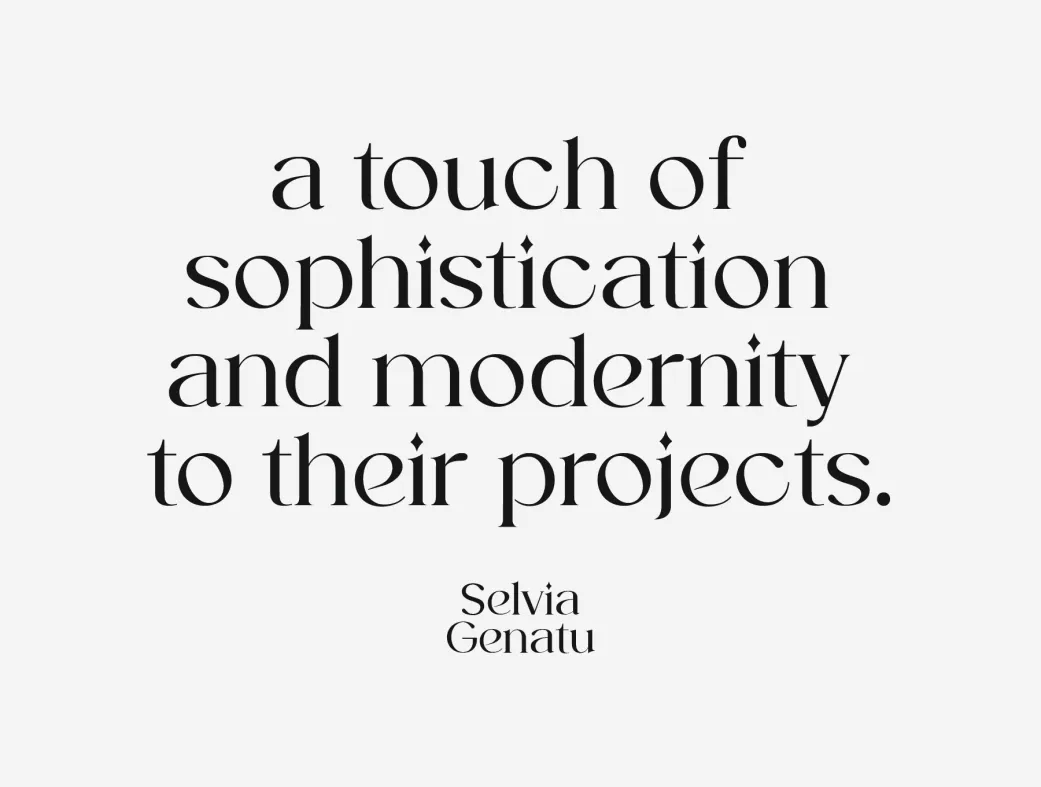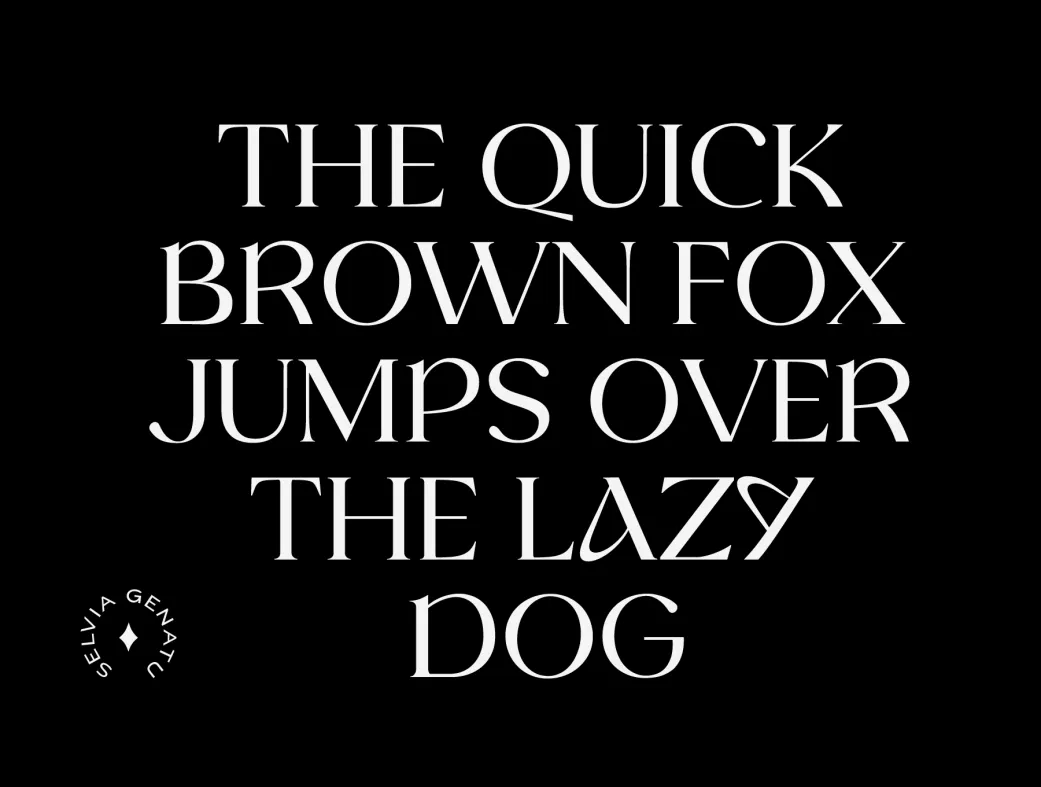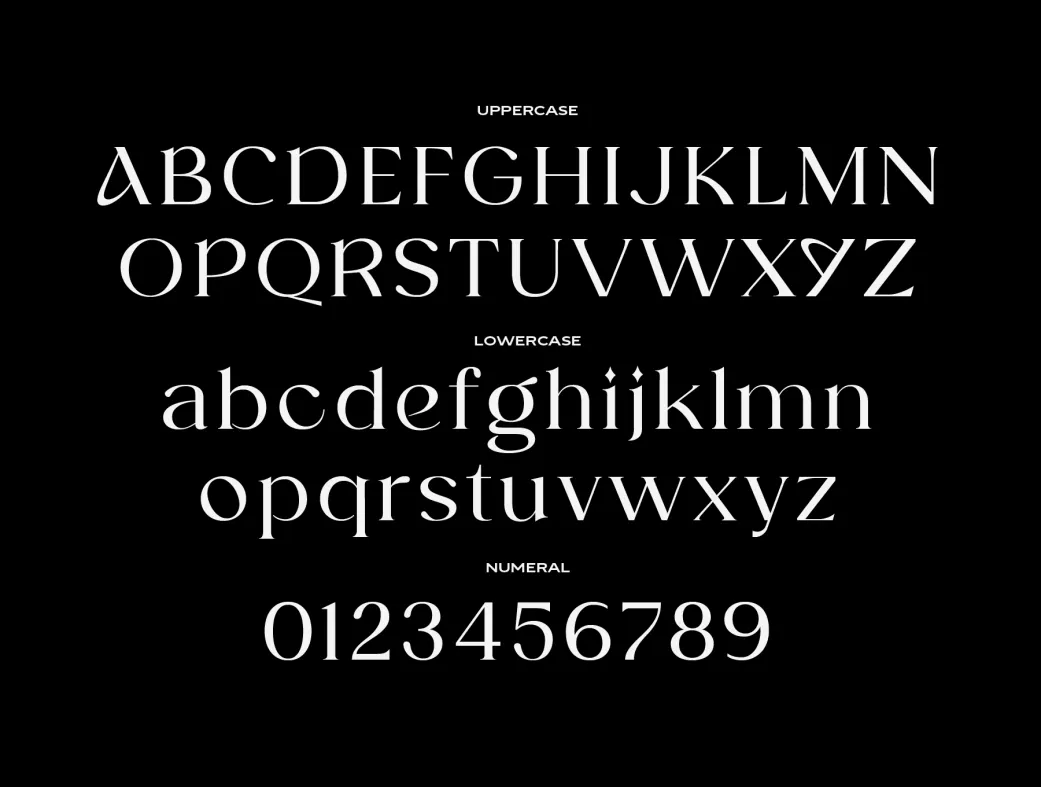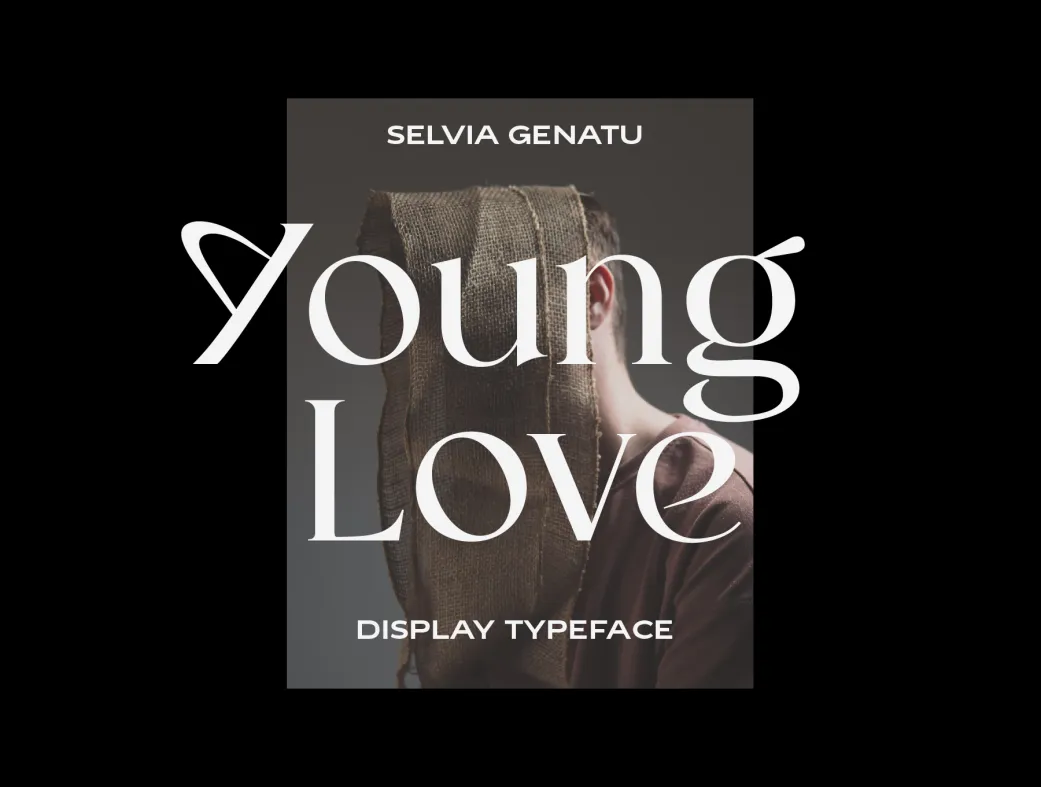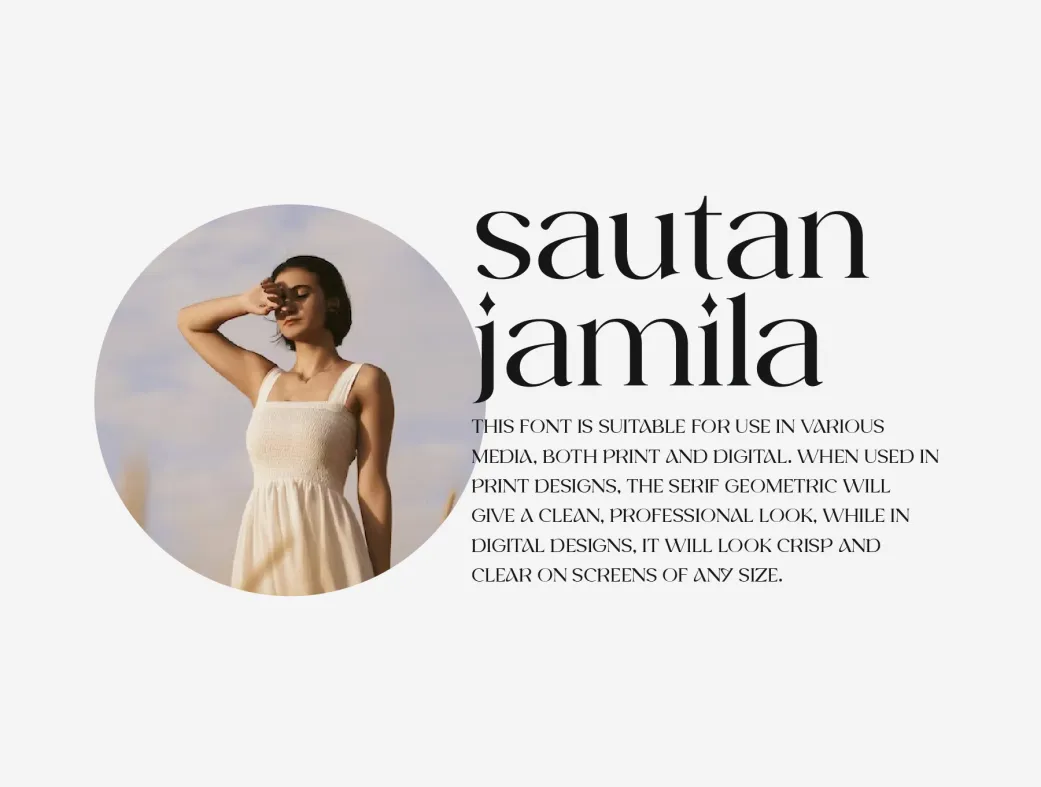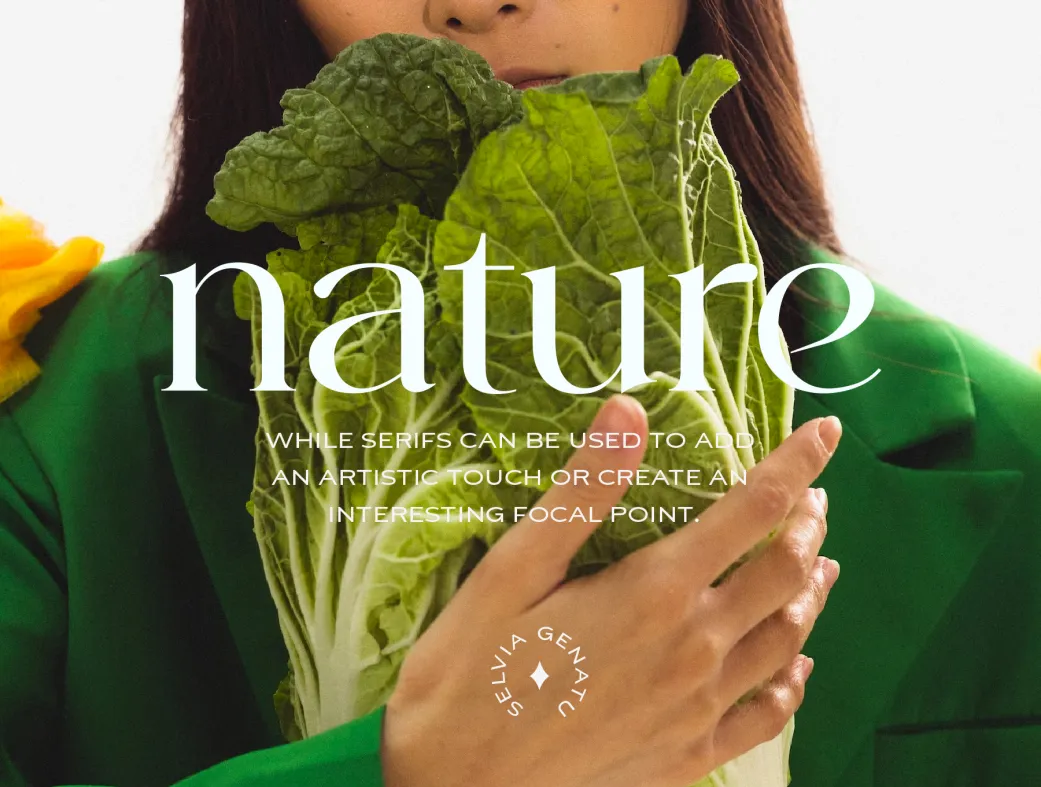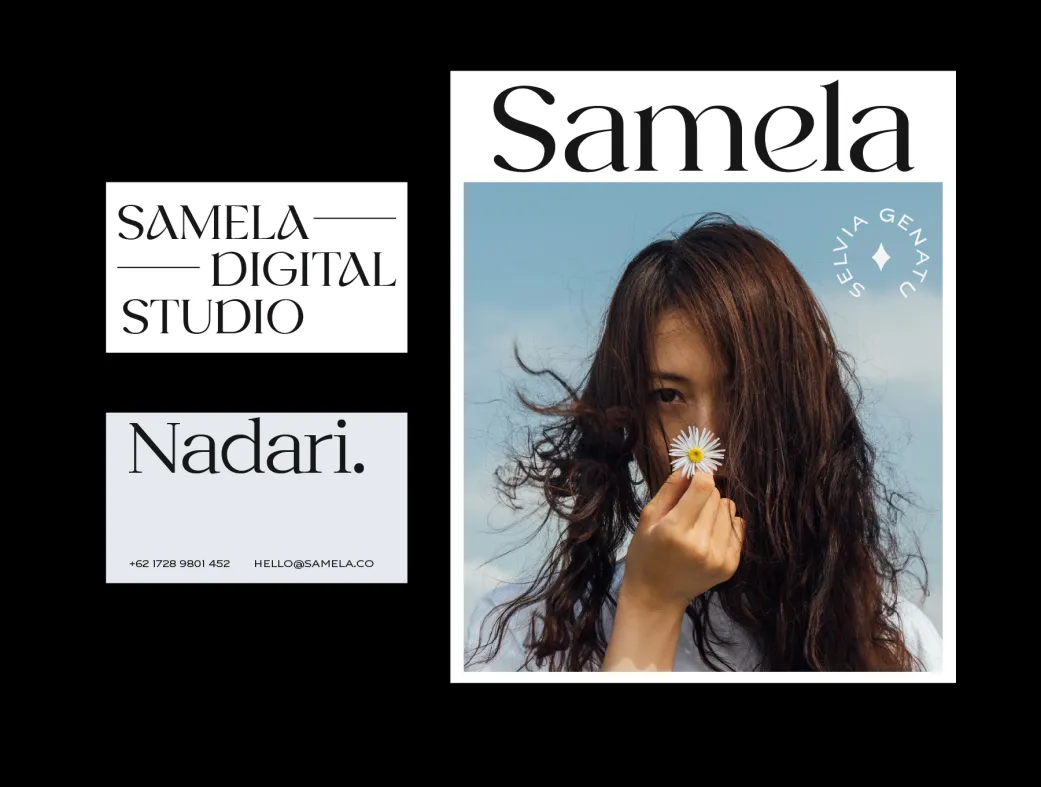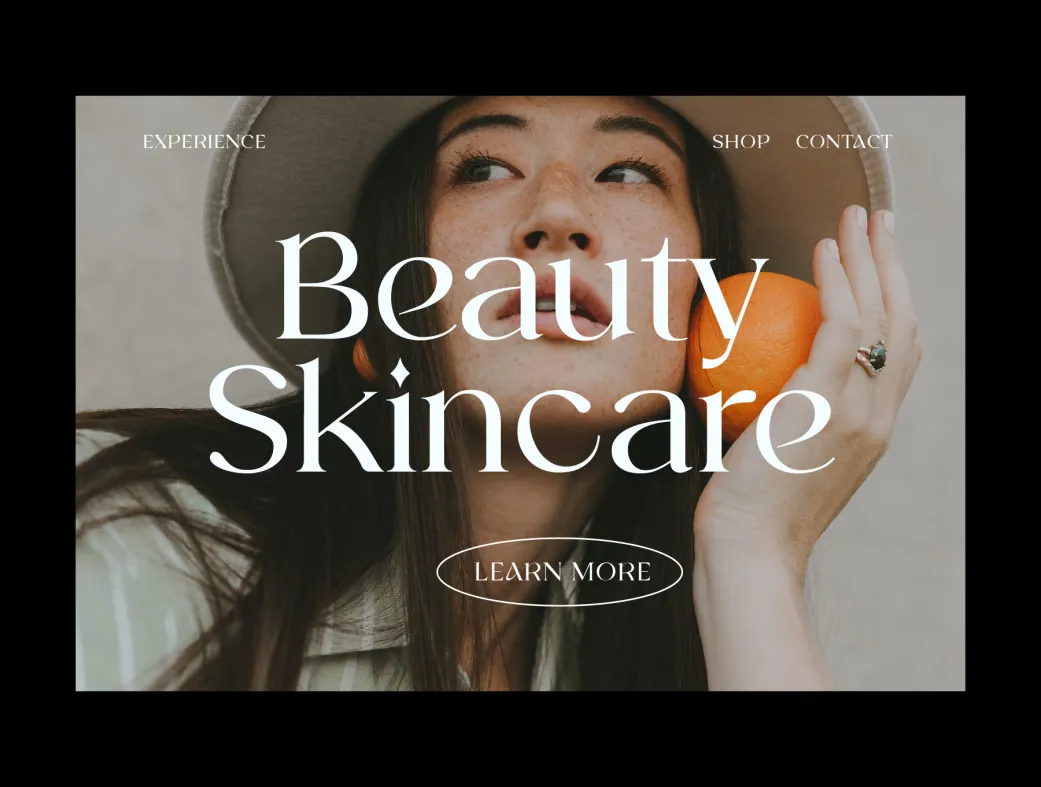
فونت سریف رایگان سلویای جنات | Selvia Genatu
آیا به دنبال فونتی شیک و مدرن هستید؟ فونت سریف سلویای جنات، جذابیت کلاسیک و انعطاف‌پذیری را به پروژه‌های شما می‌آورد!
Selvia Genatu Serif Fonts
فونت سریف رایگان سلویای جنات | Selvia Genatu | Selvia Genatu Font
معرفی محصول:
فونت سریف رایگان سلویای جنات یک فونت زیبا و شیک است که جذابیت کلاسیک را با انعطاف‌پذیری مدرن ترکیب می‌کند. این فونت با منحنی‌های نرم خود، هماهنگی بصری فوق‌العاده‌ای را ایجاد می‌کند و برای پروژه‌های متنوع از دعوت‌نامه‌های عروسی تا طراحی‌های شرکتی مناسب است.
ویژگی‌ها و مزایا:
فونت سلویای جنات تنها یک فونت نیست، بلکه یک بیانیه هنری است که جذابیت هر طراحی را با لمسه‌ای از ظرافت افزایش می‌دهد. این فونت با تناسب‌های دقیق حروف، خوانایی بهینه‌ای را در هر اندازه‌ای تضمین می‌کند. با توجه به طراحی مدرن و کلاسیک آن، این فونت گزینه‌ای عالی برای پروژه‌های گرافیکی مختلف شامل برندینگ، تبلیغات و چاپ است.
کاربردها و نکات استفاده:
فونت سلویای جنات برای انواع پروژه‌ها مانند طراحی لوگو، بروشورها، وب‌سایت‌ها و حتی دعوت‌نامه‌های عروسی بسیار مناسب است. برای بهترین نتیجه، توصیه می‌شود از این فونت در اندازه‌های مختلف استفاده کنید تا زیبایی و خوانایی آن به خوبی نمایان شود.
4. آیا این فونت برای طراحی وب مناسب است؟
بله، فونت سلویای جنات به دلیل طراحی زیبا و خوانایی عالی، گزینه‌ای مناسب برای طراحی وب است.